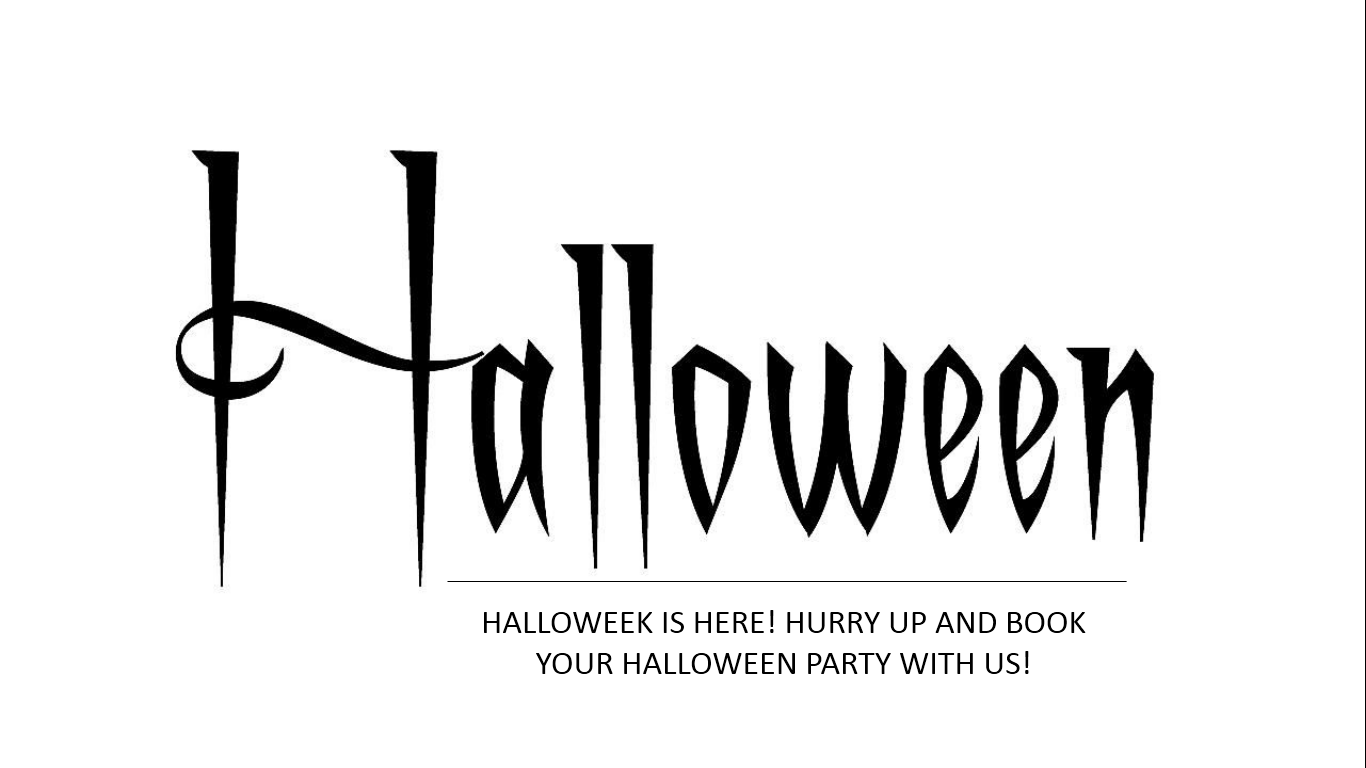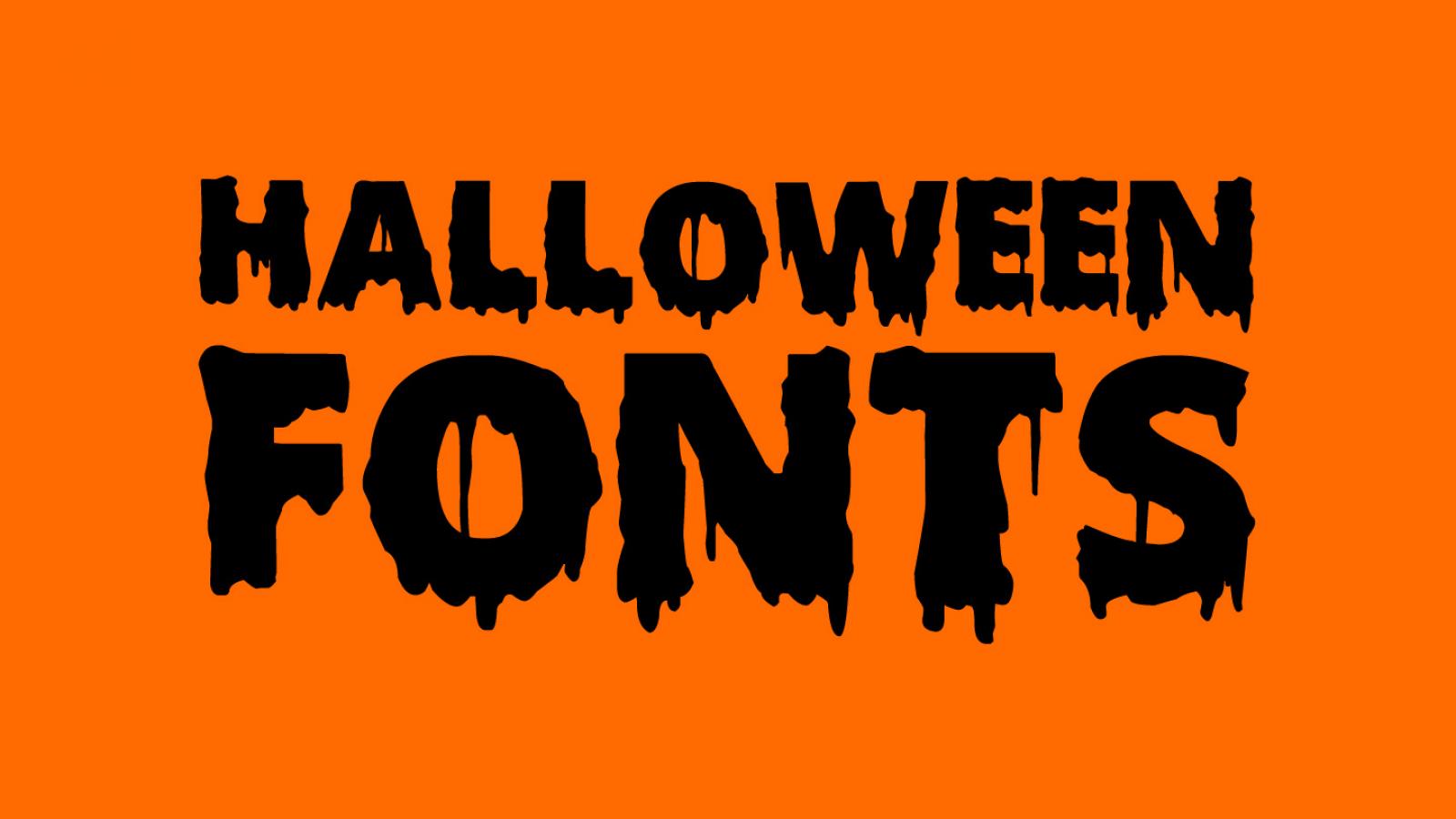
Шрифты которые хорошо подходят для оформления текстов для праздника хэллоуин.
6. Лучший шрифт зомби-апокалипсиса:
О мертвых
7. Лучший шрифт вампира/оборотня:
Оборотень Луна
8. Лучший размытый шрифт:
Погоня за призраком
9. Лучший магический шрифт:
Школа магии
10. Шрифт Best Potions:
FairydustB